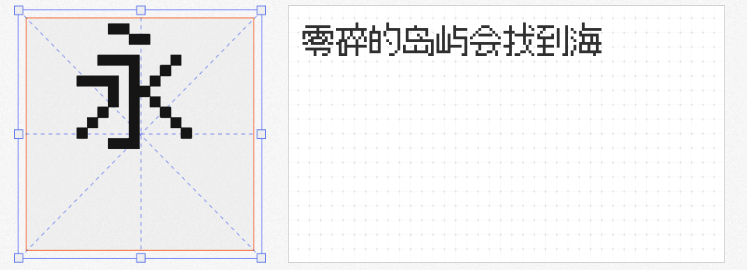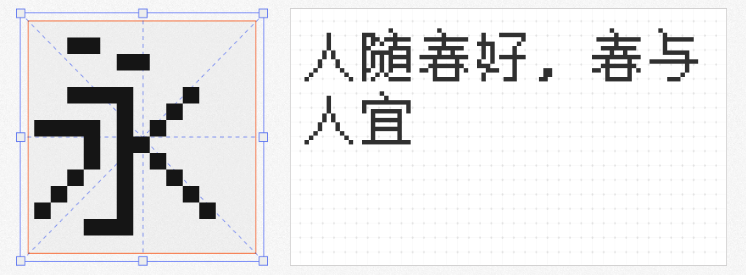
在数字设计领域,像素字体以其独特的复古风格和清晰的视觉效果,成为许多设计师的首选。无论是游戏界面、网页设计,还是品牌标识,像素字体都能为作品增添一份独特的魅力。今天,我们为大家推荐四款免费商用的像素字体,它们不仅风格各异,还能满足不同设计需求。
Mplus HZK 是一款专为中文设计的像素字体,由一位热爱字体的设计师基于 Mplus 字体的英文与日文部分,结合 HZK12 字体的特点制作而成。这款字体的设计初衷是为了填补中文像素字体的空白,同时保持字体的美观性和实用性。Mplus HZK的笔画清晰,字形紧凑,非常适合用于复古风格的游戏设计、网页标题或品牌标识。无论是中文字符还是英文字符,都能完美融合,为你的设计增添一份独特的东方韵味。
像素 Silver 是一款专为游戏设计的多语言像素字体,支持多种语言字符集,包括中文、英文、日文等。这款字体的设计灵感来源于经典的游戏界面,字形简洁且富有动感,非常适合用于游戏 UI、角色对话或复古风格的海报设计。像素 Silver 的独特之处在于其多语言支持,能够满足国际化项目的需求,同时保持像素字体特有的复古魅力。
寒蝉点阵体 7px 是一款基于日文字体「美咲フォント」改造的中文像素字体,融合了「精品點陣體7×7」和「Guanzhi 8px」的部分字形设计。这款字体的特点是字形清晰、结构紧凑,特别适合用于小尺寸的显示场景,如游戏界面、电子书或移动应用设计。寒蝉点阵体 7px 的英文部分和标点符号经过重新设计,与中文字符更加协调统一,整体视觉效果非常耐看。
DOSPilgi 是一款由韩国设计师 Damheo Lee 制作的像素字体,灵感来源于经典的 DOS 操作系统界面。这款字体的设计基于位图二进制数据,字形方正且富有科技感,非常适合用于复古风格的科技类设计项目,如游戏、海报或品牌标识。DOSPilgi 的独特风格能够为你的设计增添一份怀旧气息,同时又不失现代感。